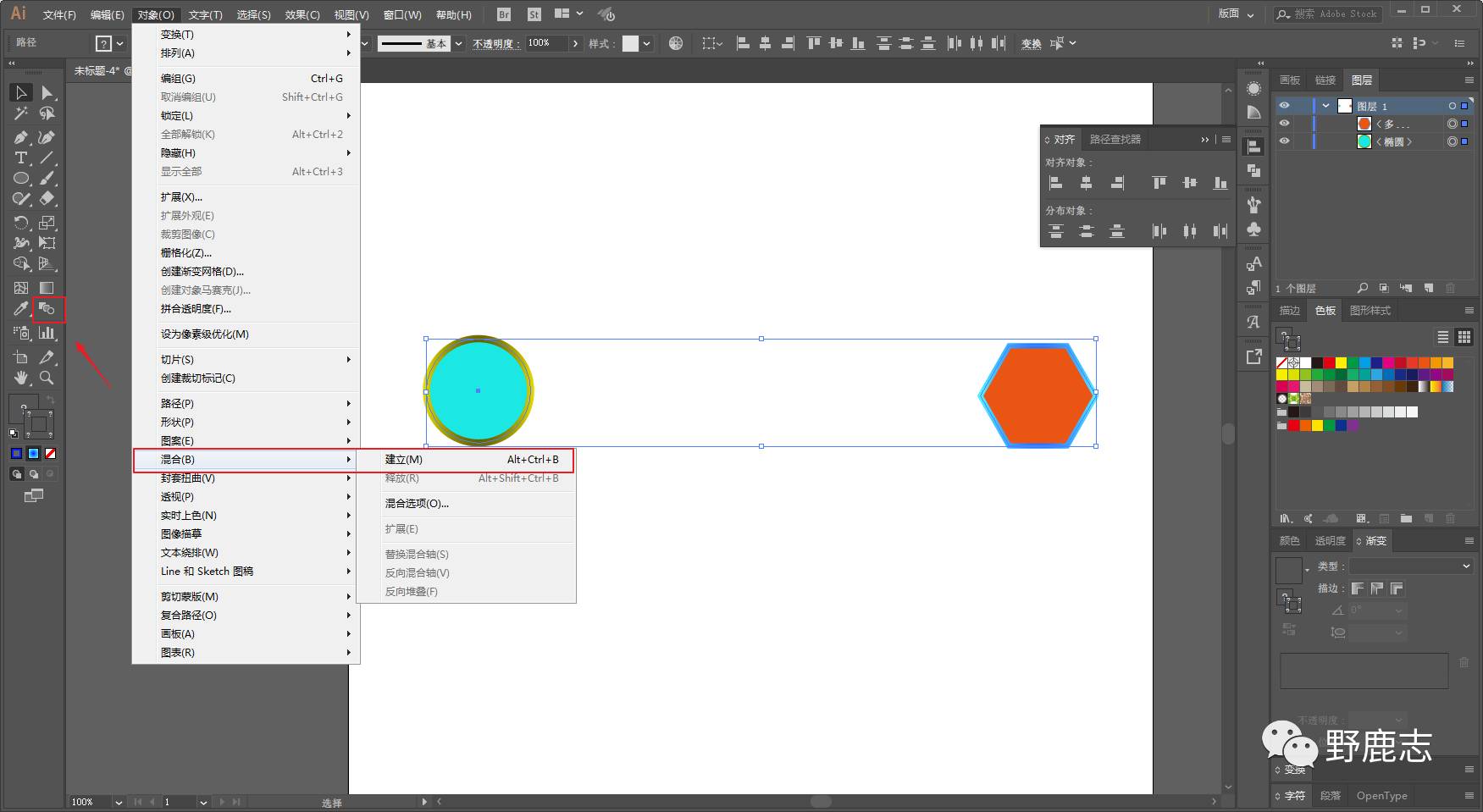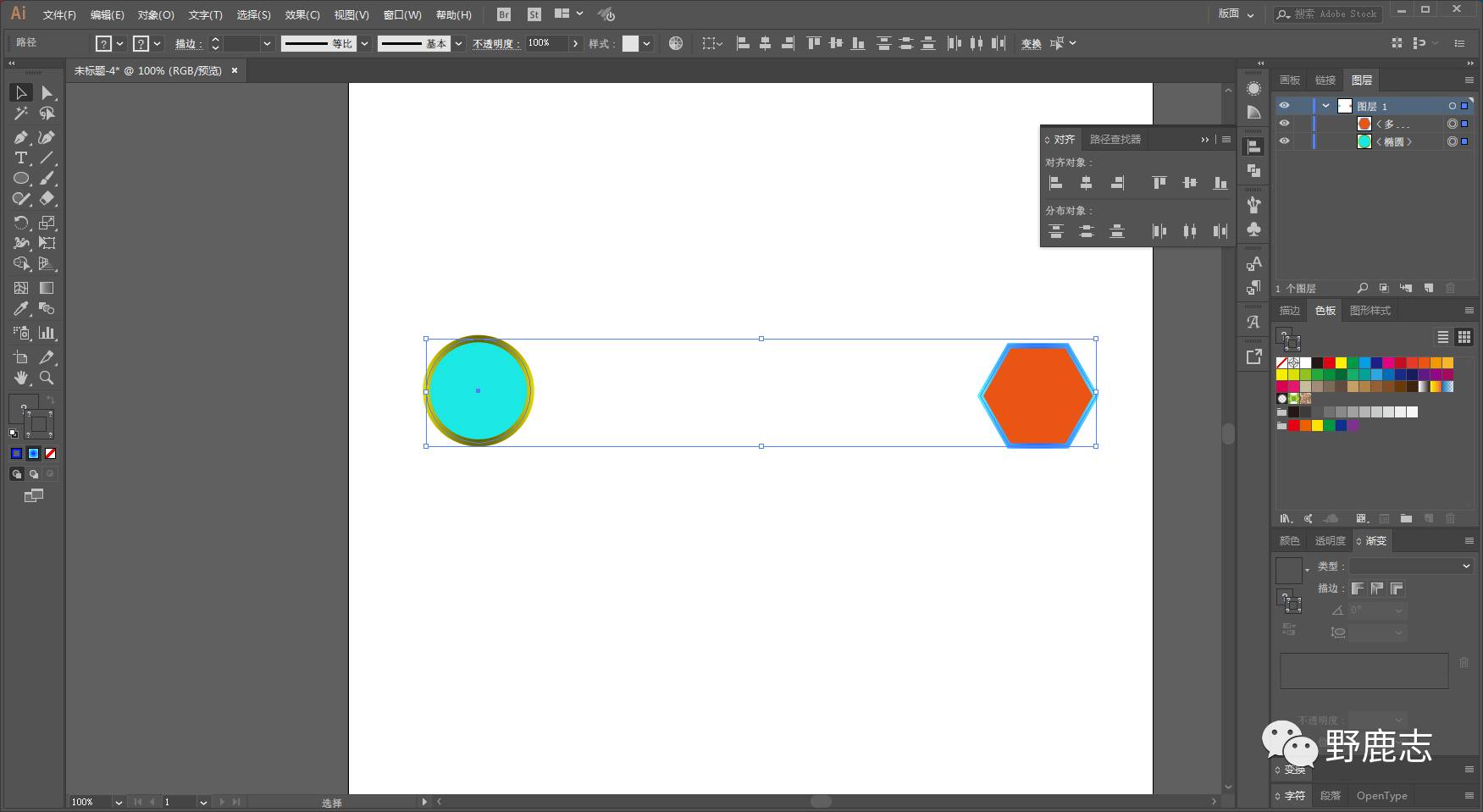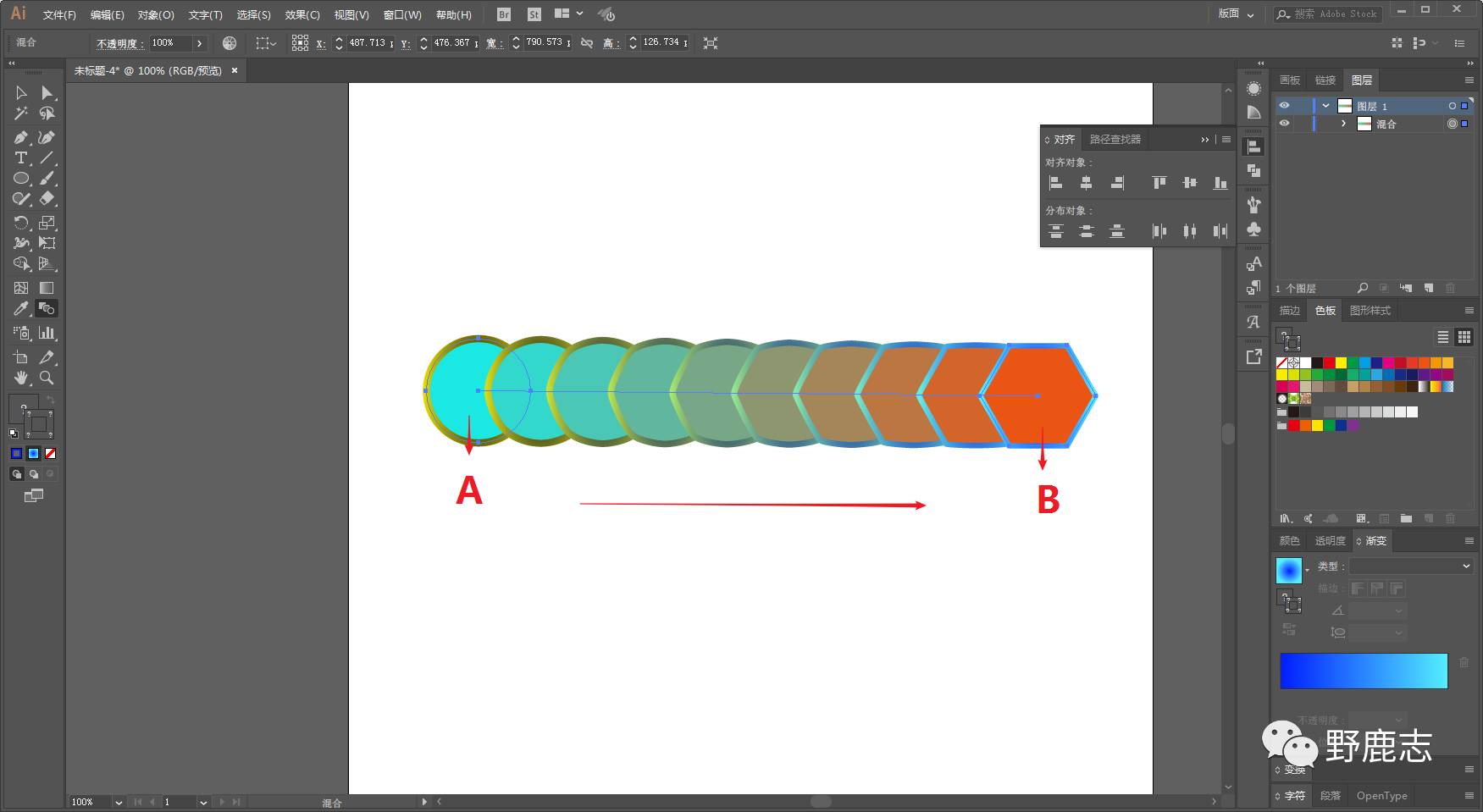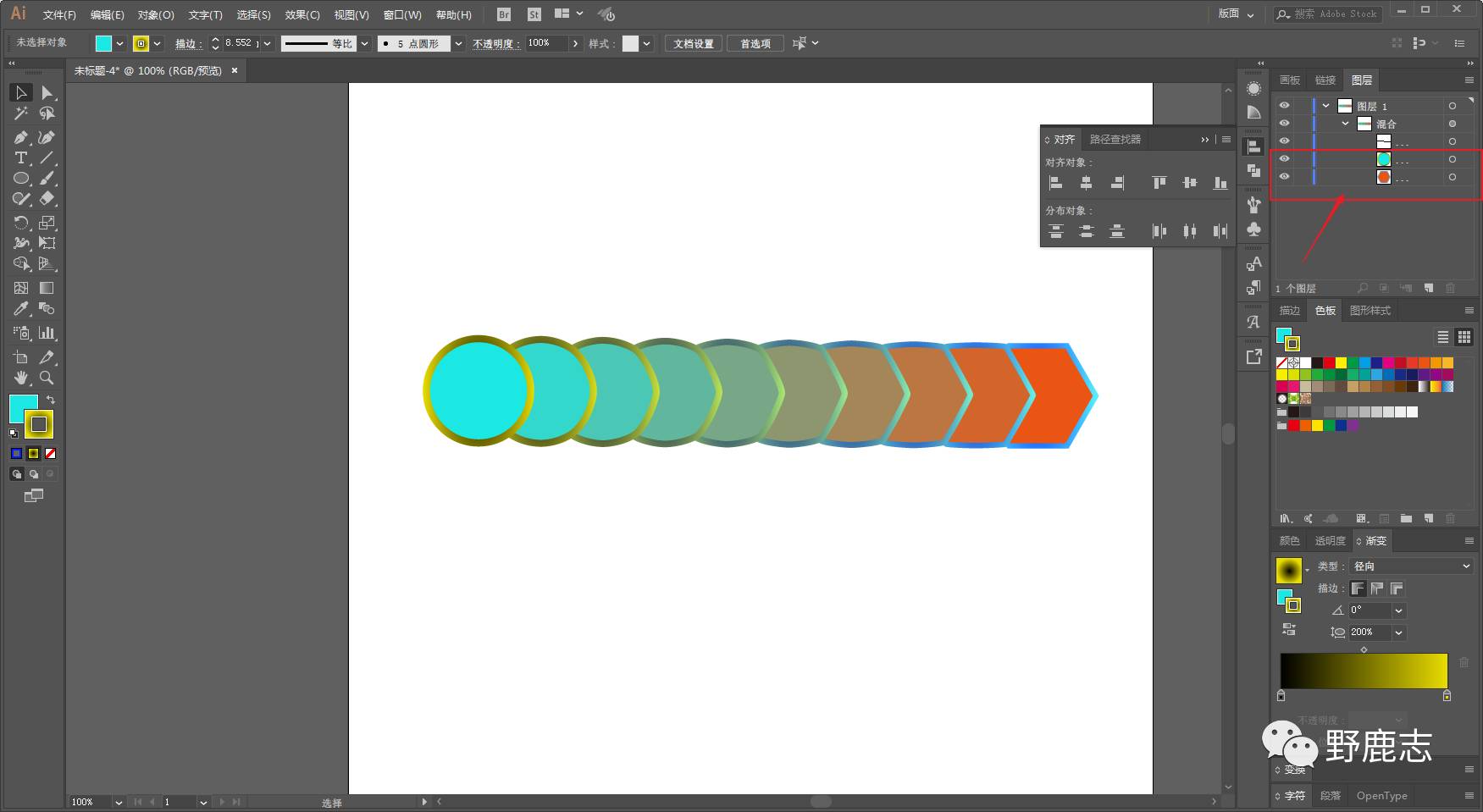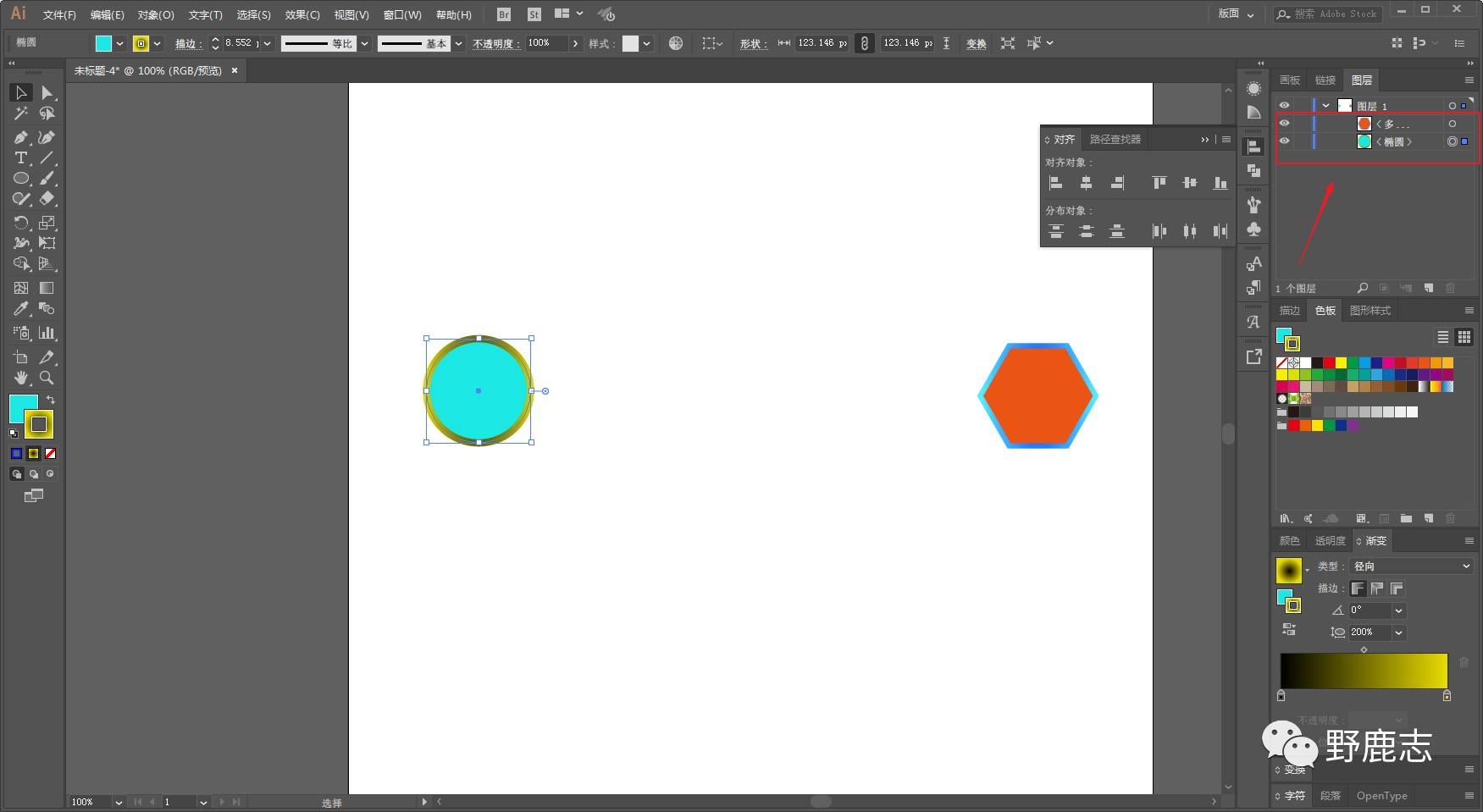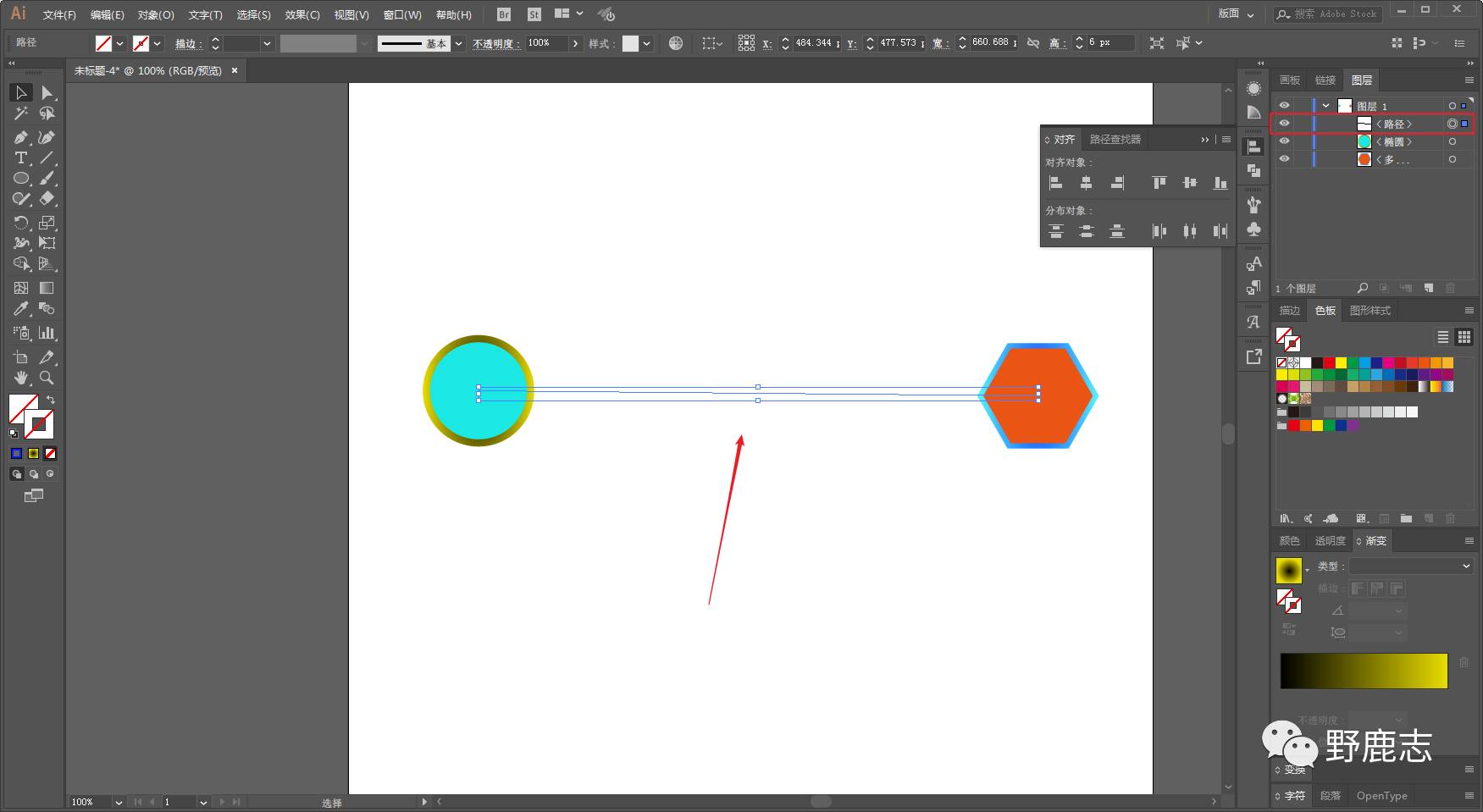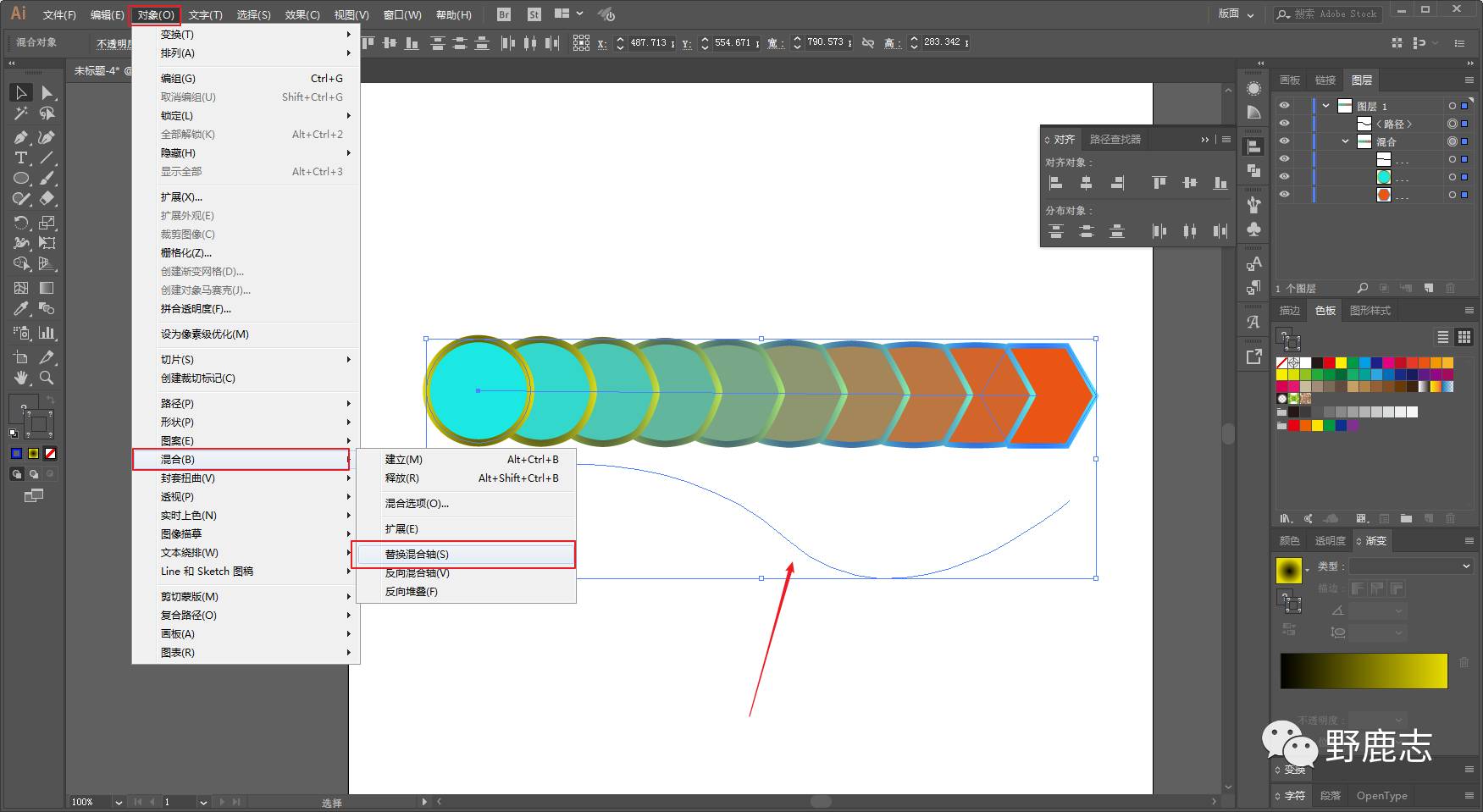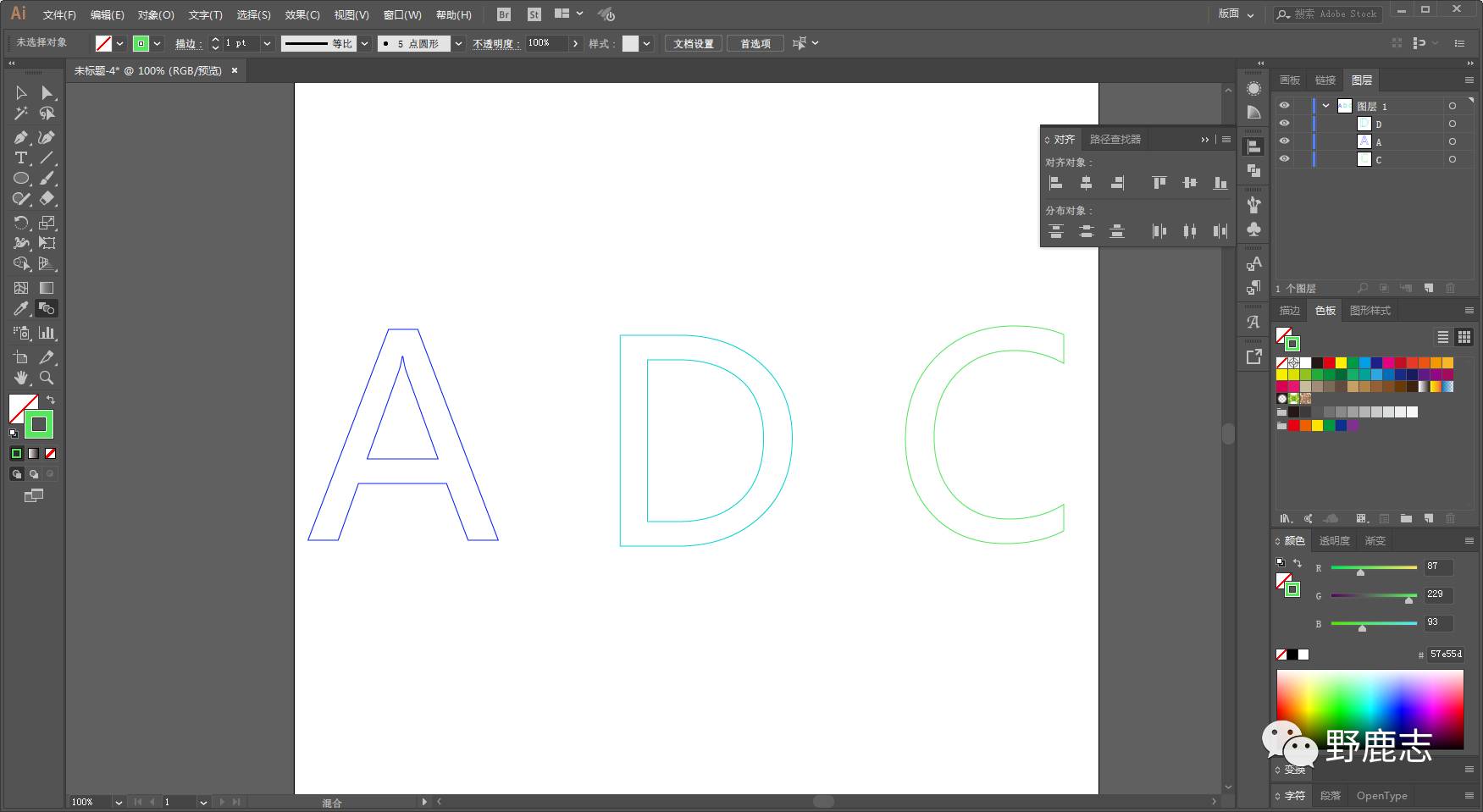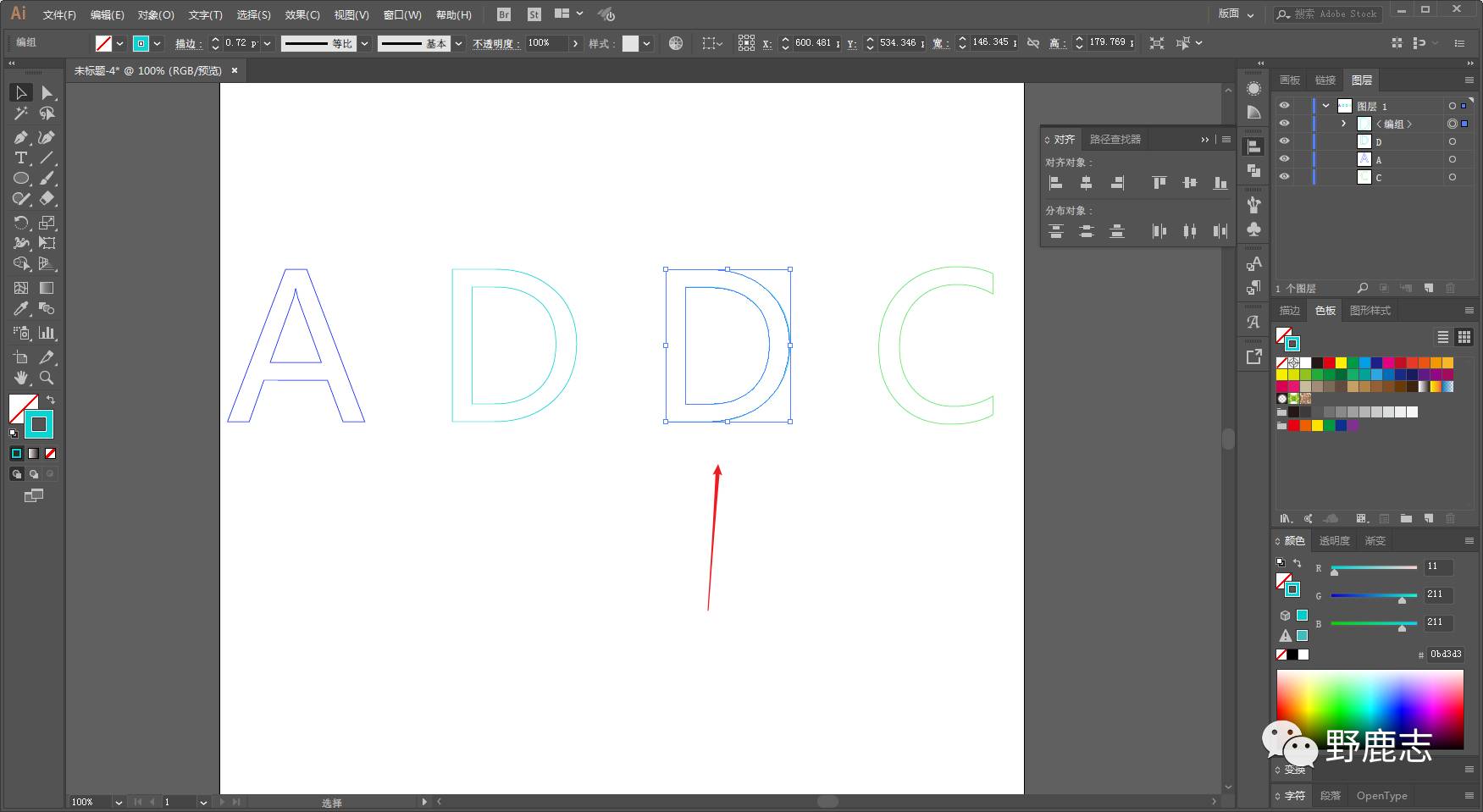
AI 混合工具实例运用 混合大法好啊!
好了,来看问题吧:
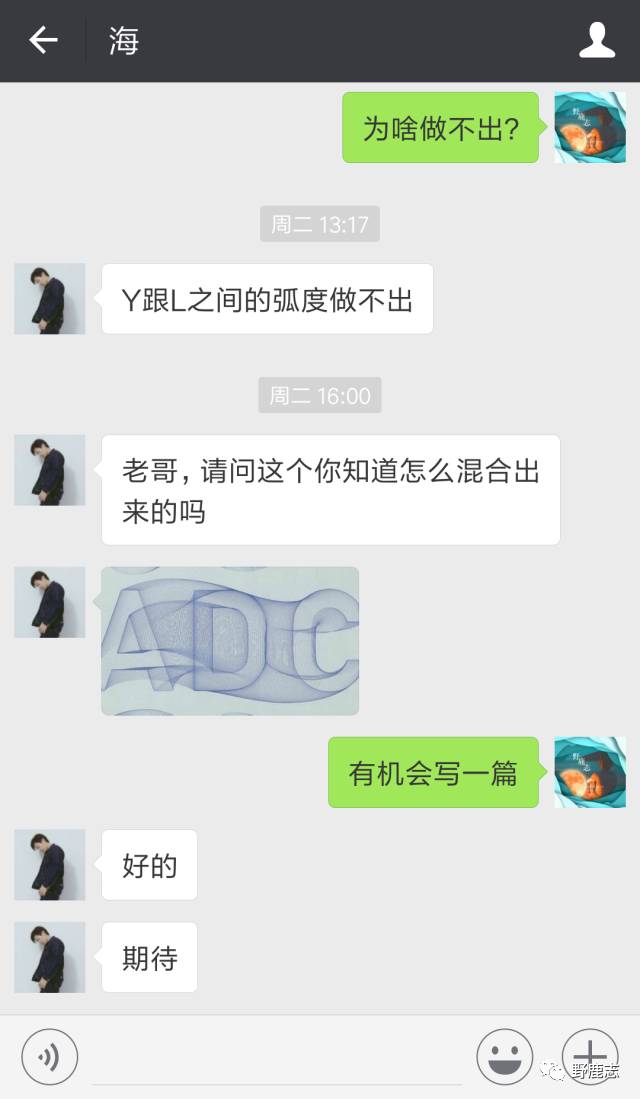
其实海童鞋都已经知道是用混合工具做的,可能只是不太清楚具体怎么操作。
之前野郎其实也分享过几篇用到了混合工具的文章,但是并没有对工具本身进行说明。
再加上群里有些童鞋也刚开始学习Ai操作,所以我打算借着这个案例再把混合工具的用法分享一下。
开始之前还是简单的说一下混合工具的用法吧,用比较野路子一点的说法就是:
混合工具可以呈现让对象A(形状、描边、颜色)根据你的路径和设置变成对象B(形状、描边、颜色)甚至更多对象的过程。
例如我画了两个不同的形状,并且添加了描边以及颜色:
混合工具可以在左侧工具栏以及对象-混合中找到,如图所示:
当我用鼠标单击左侧工具栏中的混合工具图标后,再先后单击A和B,它就会如之前所说呈现出从A变成B的过程,包括形状、颜色以及描边:
这里有一点特别提示一下是对象的图层顺序,如图所示六边形是在圆形的上方:
当我们调换了圆形和六边形的图层顺序以后,再混合一次,大家可以看看差别:
因此为了达到自己想要的效果,大家在混合前可以先思考一下谁在前谁在后。
除此之外,刚才我们提到了混合工具是根据你的路径以及设置进行混合,例如我这里混合了以后将选中对象将混合进行释放:
大家可以看到这里就多出了一条路径来,它的圆形其实就是这两个对象根据这条路径进行混合。
另外说一下,混合的路径默认都是直线哦:
所以如果你希望它跟随你自己绘制的路径进行混合,只需要如图再绘制一个路径,然后全选中对象以后执行对象-混合-替换混合轴:
混合的路径就会替换为你绘制的曲线路径了。
另外你可以双击混合工具图标调出混选项进行参数的设置,我一般用的比较多的还是步数的设置,其他两个选项用的比较少:
使用方法知道了以后,我们再回头看看海童鞋的问题,如图所示先打上三个字母,记得是无填充有描边,颜色就自己随便选吧:
混合步数的话,大家看着来就好,海童鞋的这张案例图应该是在混合上做了一定的修饰。
因为如果是直接混合的话,大家可以看看会变成这样:
分析一下原因,将对象扩展取消编组以后,用小白工具指向这个地方,你会发现它其实是一个一个的D字母组成的:
这个应该是由于D这个字母是内侧形状导致,所以我想到可以把D这个字母在混合前再复制一个出来,并且ctrl+shift+o轮廓化:
用小白工具单独删除内部的描边:
再用混合工具去单独混合它们:
然后用钢笔分别画两条曲线:
对两条路径以及混合后的对象分别执行替换混合轴:
用移动工具把他们摆放在一起:
再用小白工具去调整路径的锚点和手柄以达到满意的效果就行了:
大概方法就是这样,混合工具确实是一个非常好玩的工具,简单的操作也可以让图看起来很有味道。
例如我这里排版了一些文字,画板上的是描边,旁边的是填充,描边0.01pt:
将画板上的描边文字ctrl+shift+o轮廓化,然后取消编组。
将混合步数设置为50步,然后分别选中每一个横排的文字执行ctrl+alt+b进行混合:
选中所有混合对象,执行对象-扩展,然后取消编组:
再用小白工具去单独选择部分想要继续混合的文字就可以了。
为了保证准确的选中对象,你可以把小白工具放在对象上面,即将选中的对象会以蓝色显示出来,如图:
再选中这些对象降低一点不透明度:
再观察一下红色方框出的横线,由于是有相当的字母E混合,重复的笔画导致那个横线很碍眼,不是很好看:
所以我们只需要用小白工具框选住对象,然后点击路径查找器中的差集即可:
接下来再选中之前准备好的填充文字,ctrl+shift+o轮廓化并取消编组,略微的调整一下字形,例如我这里把字母的尖角都调整成了圆弧:
再把他们移动到混合的上面大概这样啦:
最后背景上画点几何图形当点缀,老三样看看效果吧:
很简单吧,利用混合工具可以制作出很多有意思的图来,大家可以多去试试!